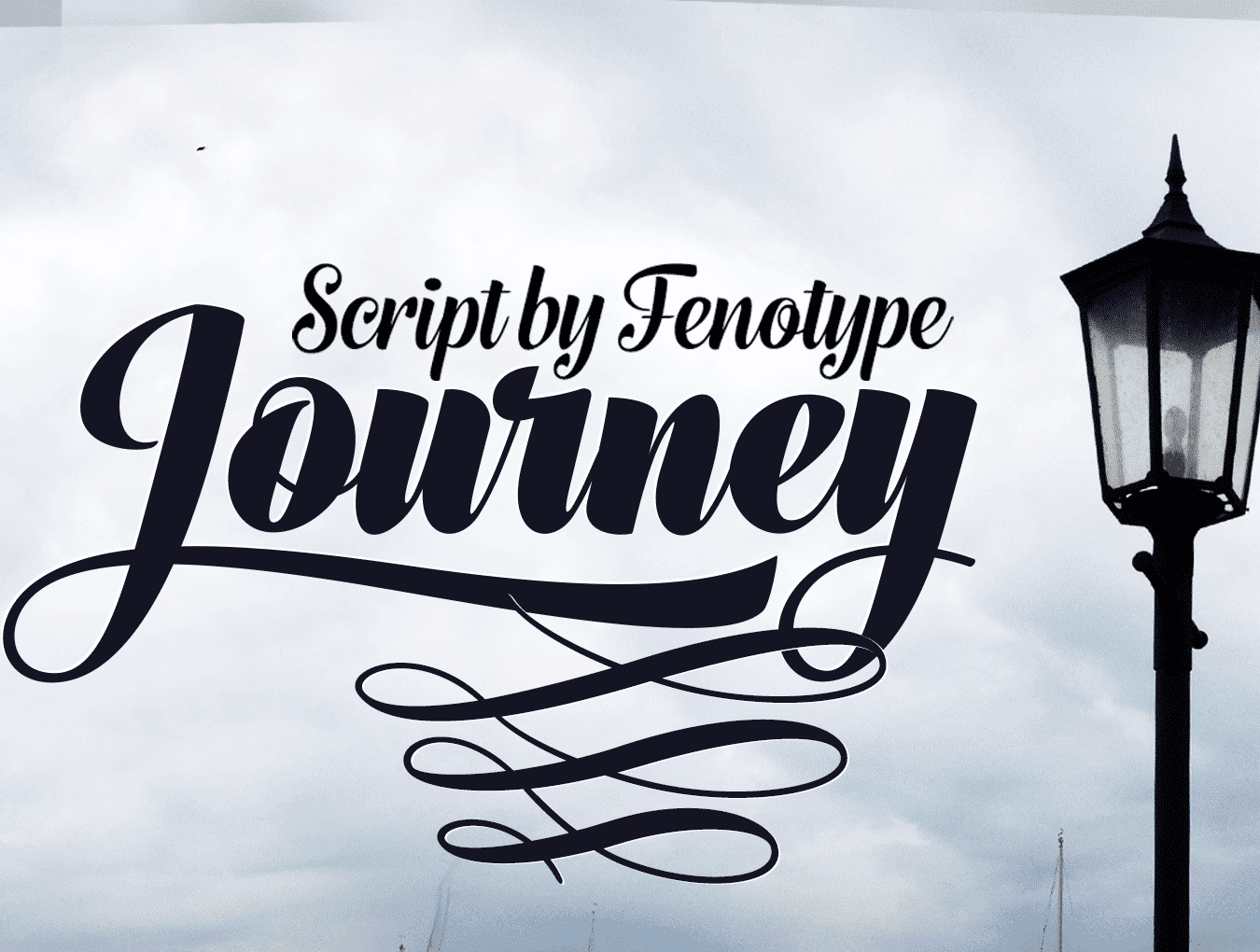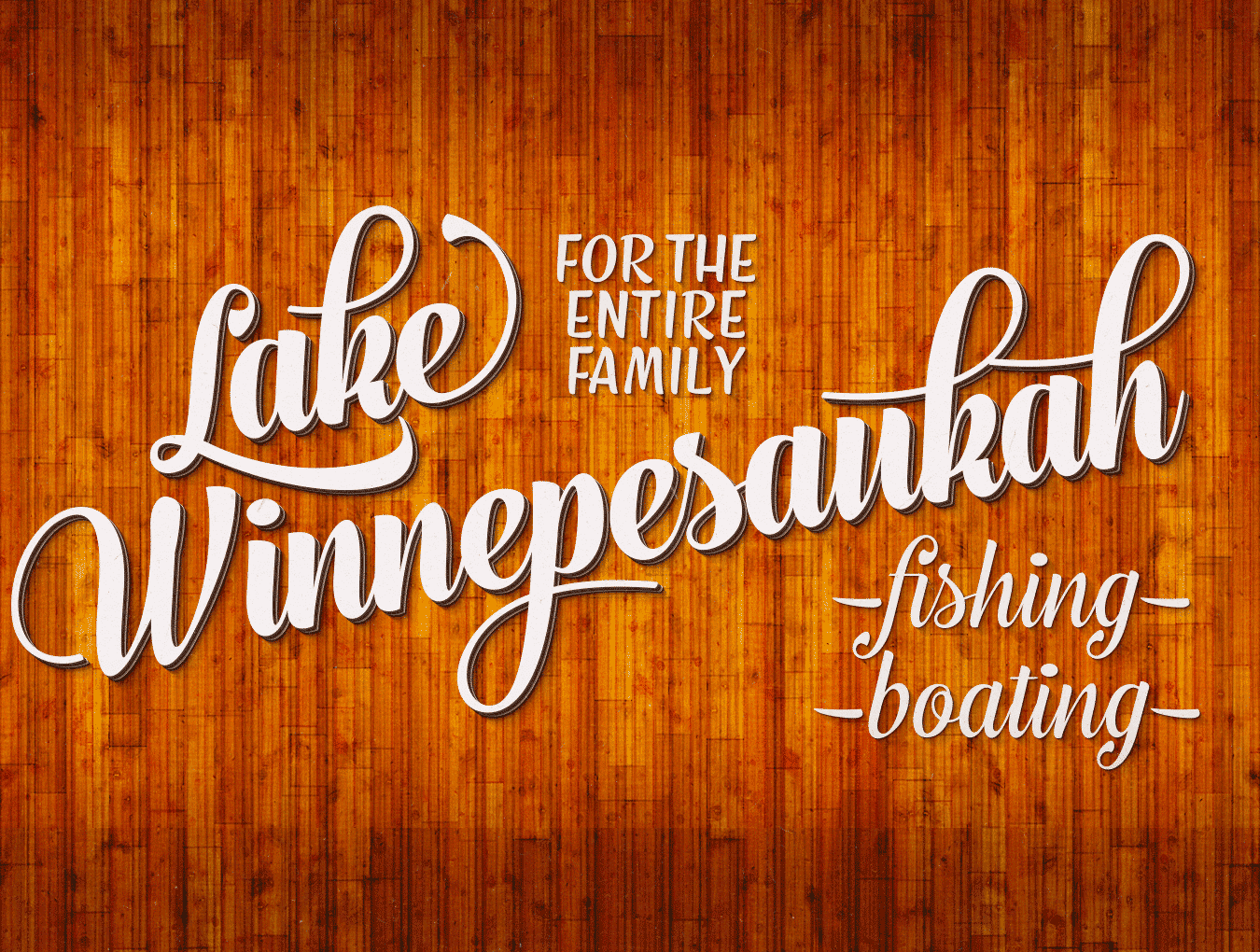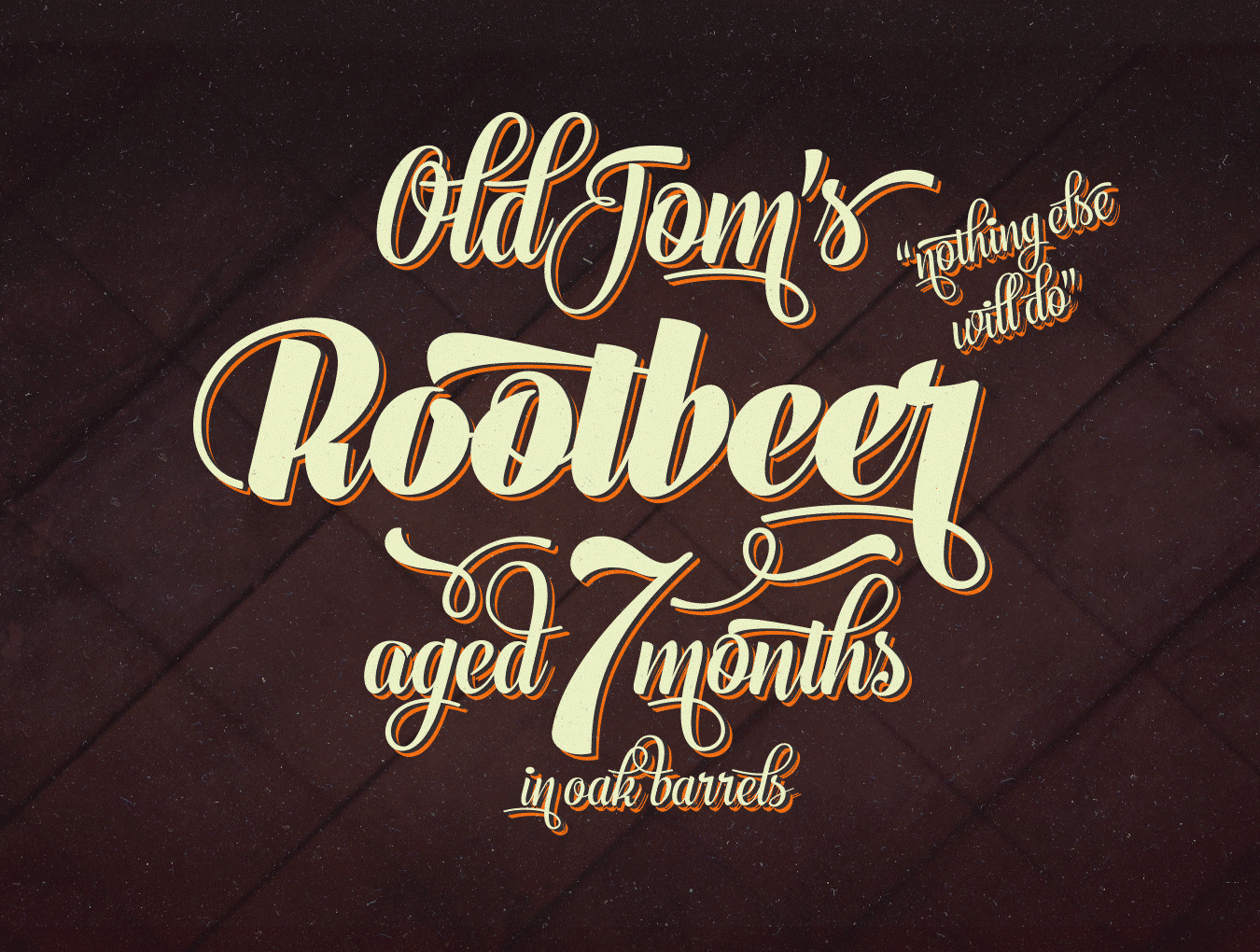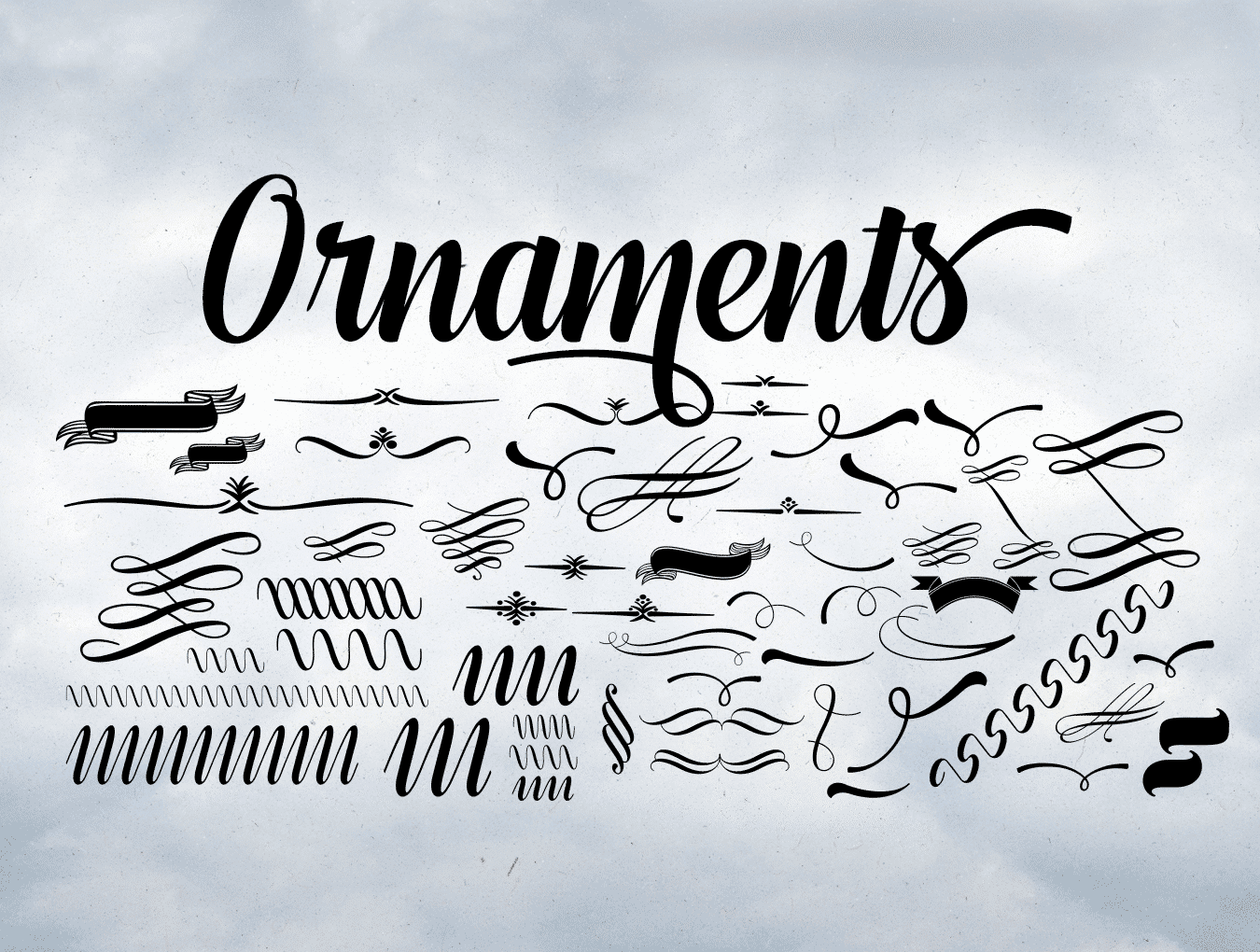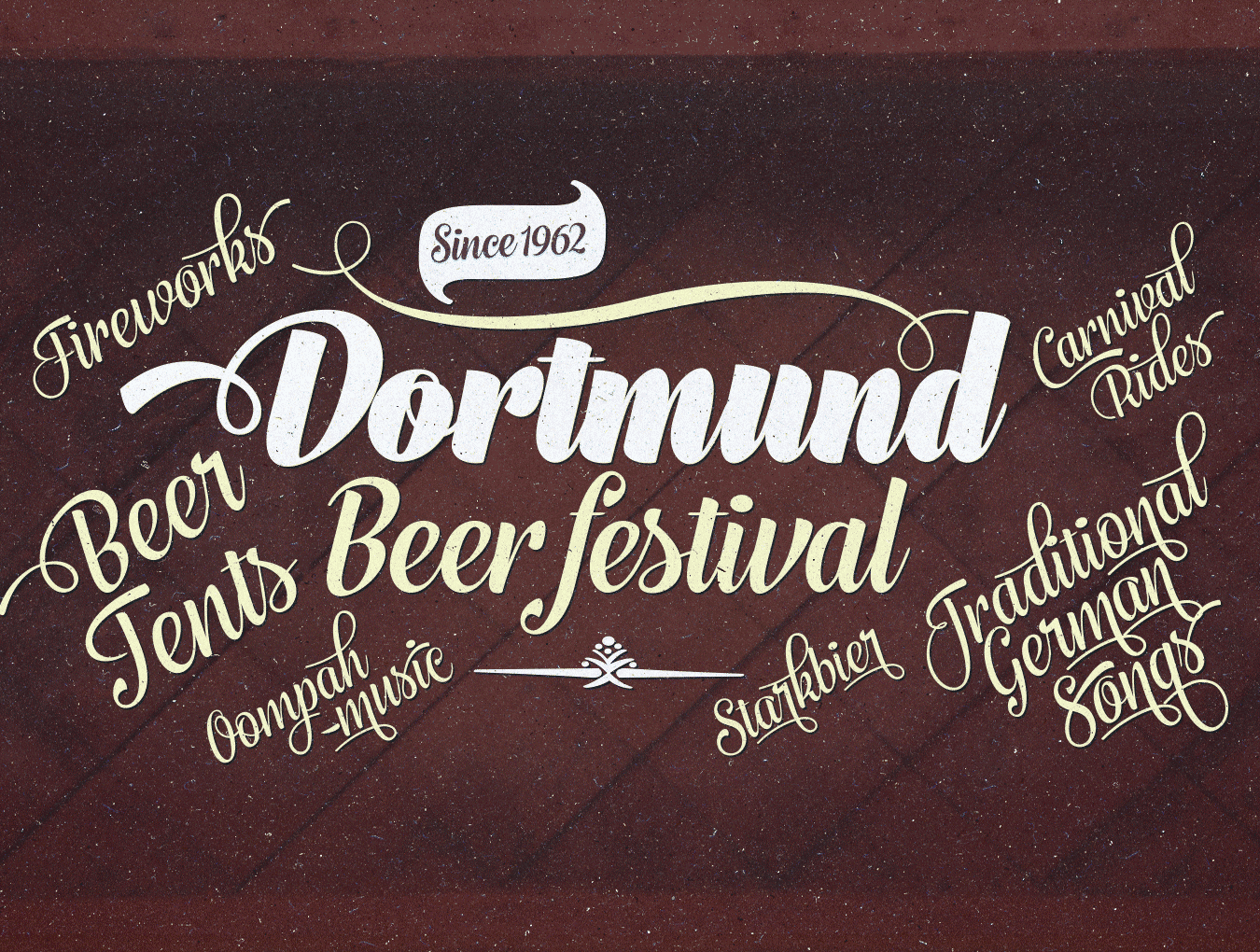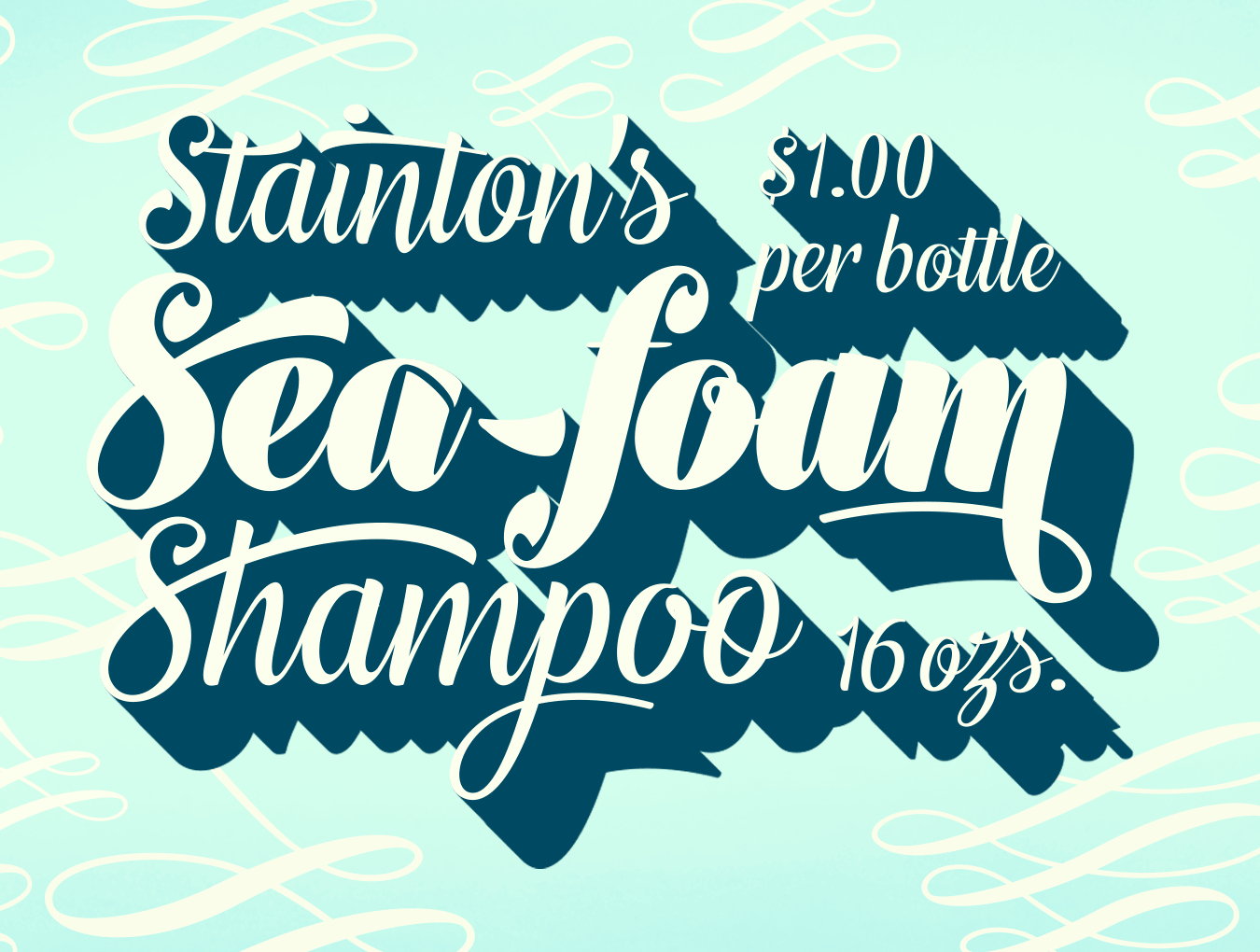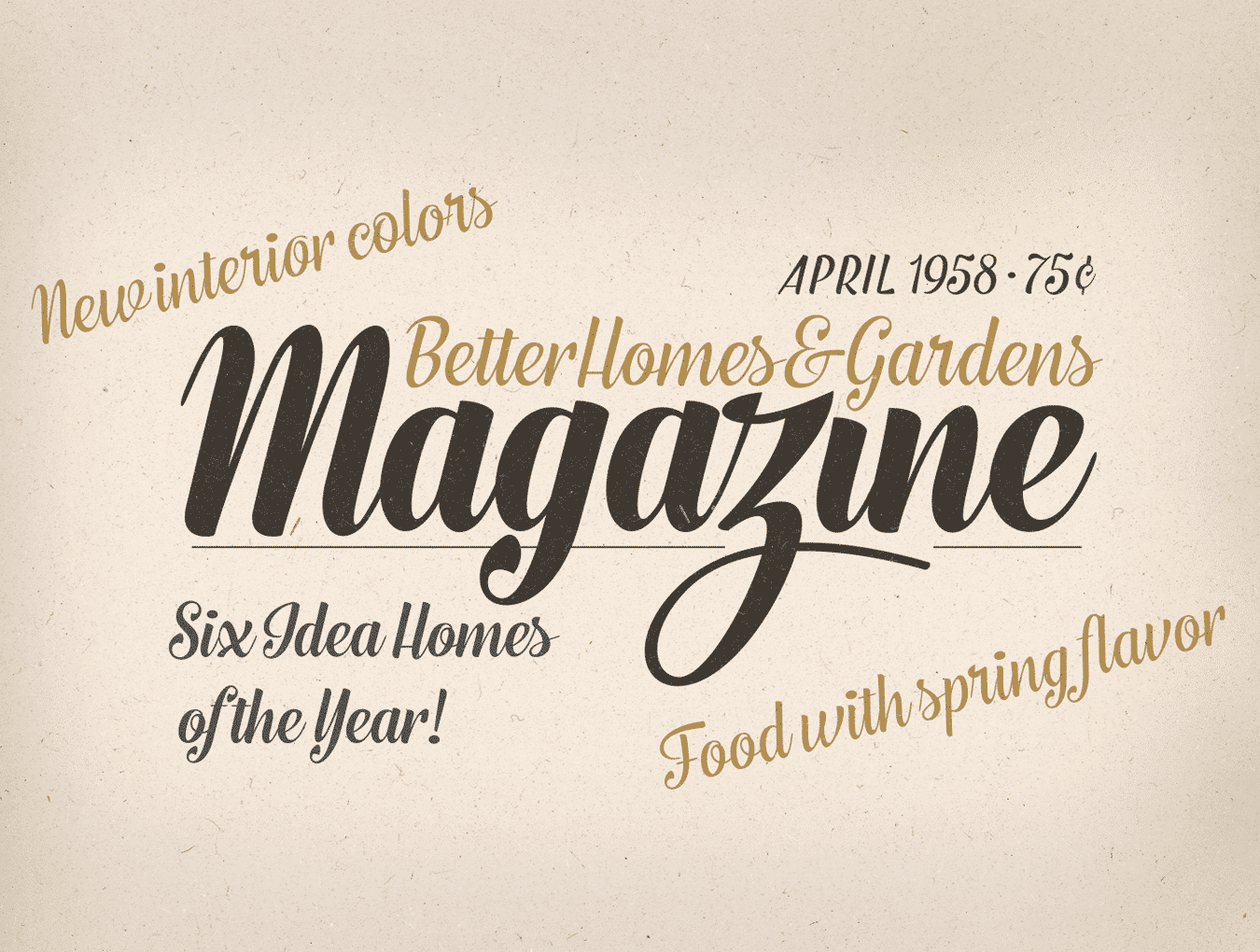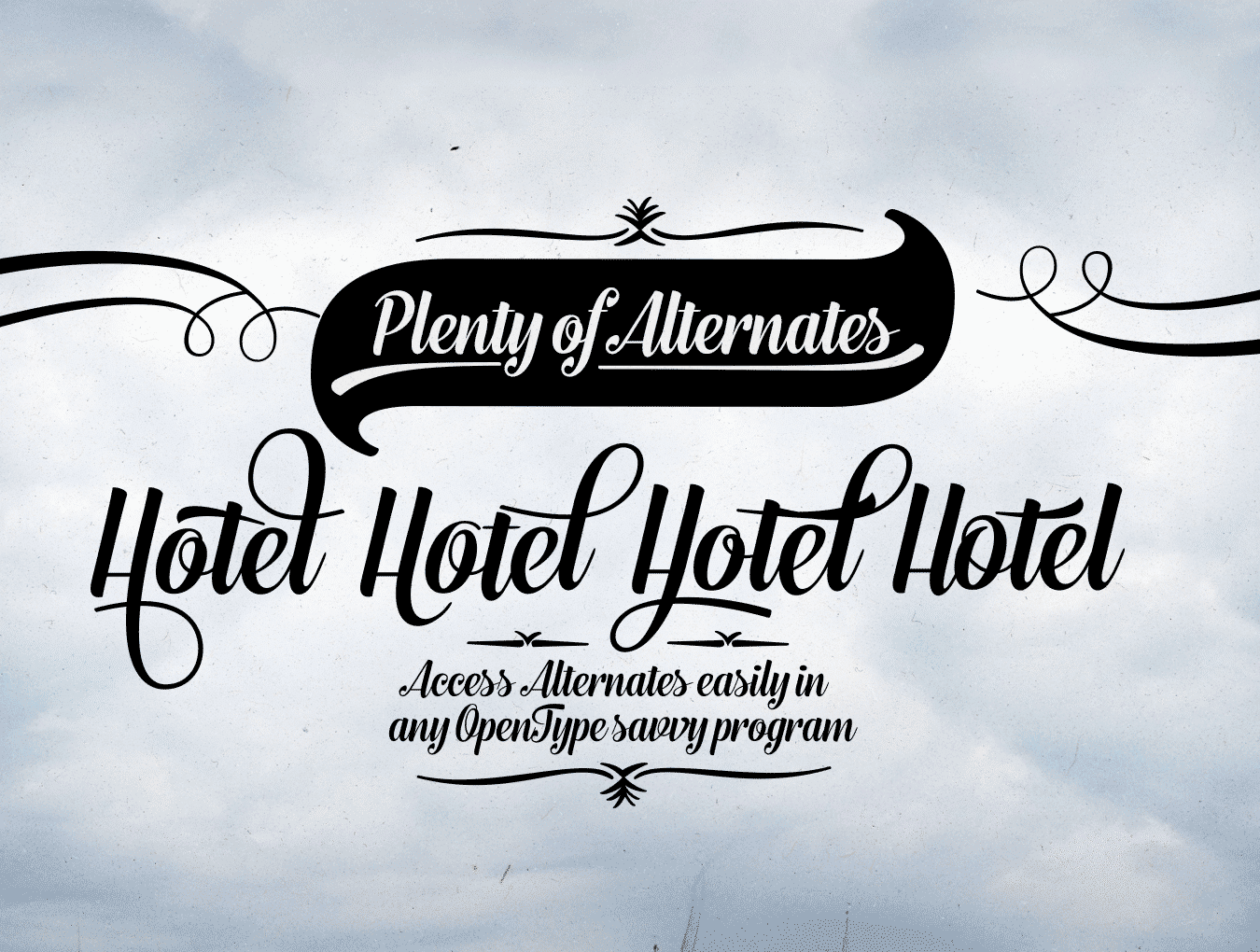
流畅优雅的复古脚本,Journey
Journey是一款流畅优雅的复古脚本系列,由四个重量和一套配套装饰组成。 Journey充满了Alternate角色,让您轻松创建具有定制感的标题,徽标和海报。 Journey至少有三个替代每个基本字母:要激活替代品,请在任何OpenType Savvy程序中单击Swash,Stylistic或Titling Alternates,或者从Glyph Palette中手动选择更多替代字符。